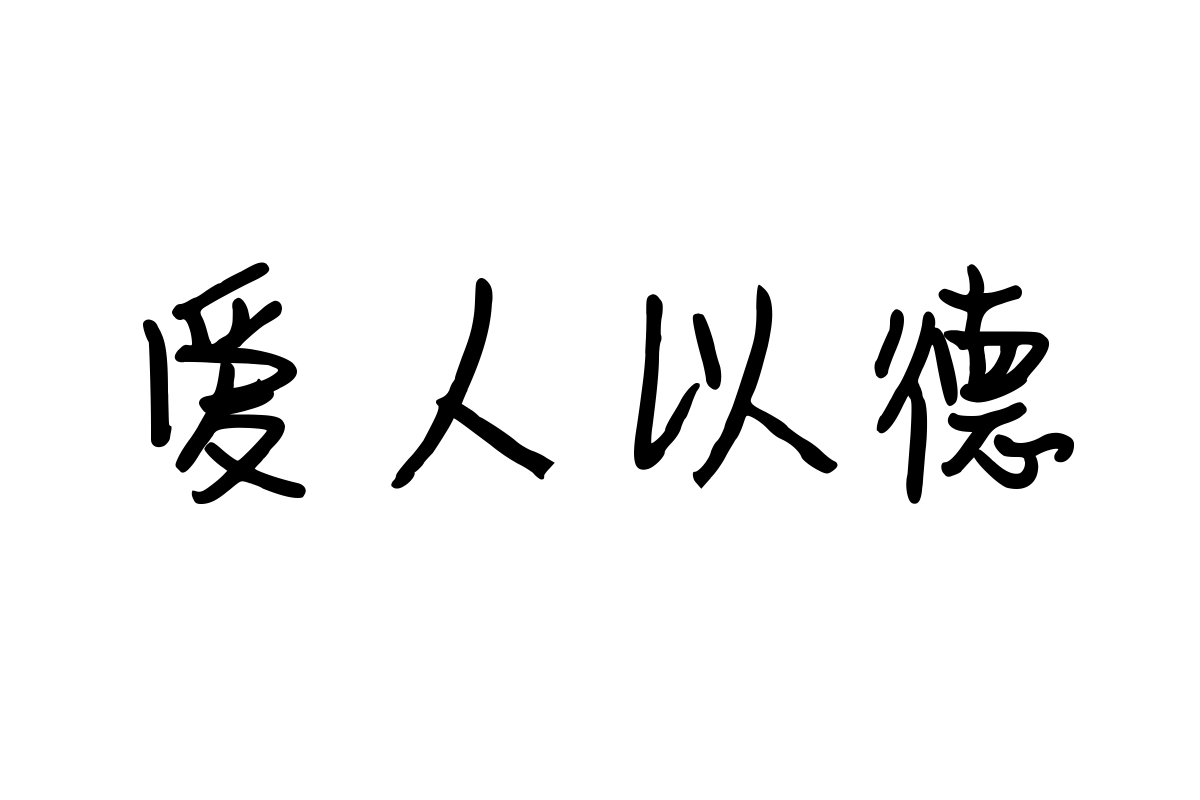
字体管家青葱体是一款现代感十足的中文字体,具有独特的设计风格和视觉效果。它采用了简洁而流畅的线条,使得整个字体看起来既优雅又大方。同时,青葱体也注重细节的处理,每一个笔画都经过精心打磨,使得整体效果更加和谐统一。
此外,字体管家青葱体还具有一定的可读性,无论是在正式的文档还是在日常的聊天中,都能展现出良好的视觉效果。它的使用范围广泛,适用于多种场景,如广告设计、网页制作、PPT展示等。
总的来说,字体管家青葱体是一款非常实用且美观的中文字体,适合各种需要展现个性和品味的设计场合。